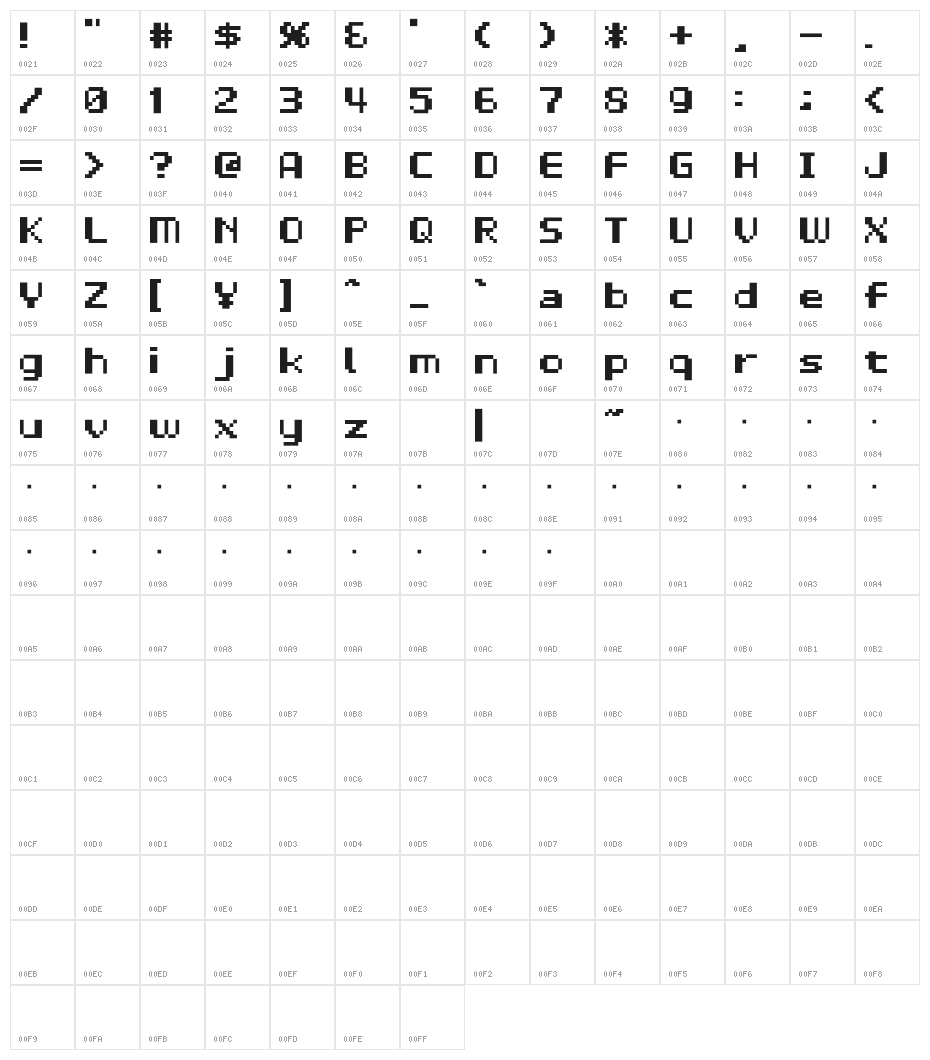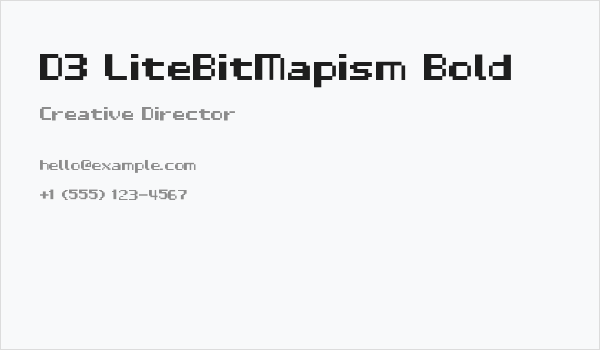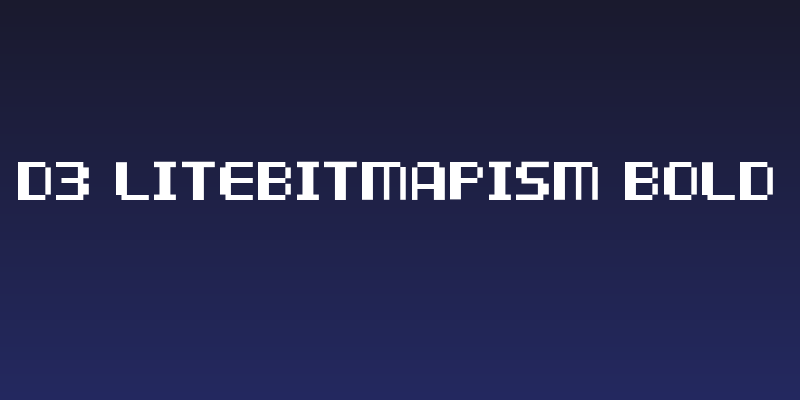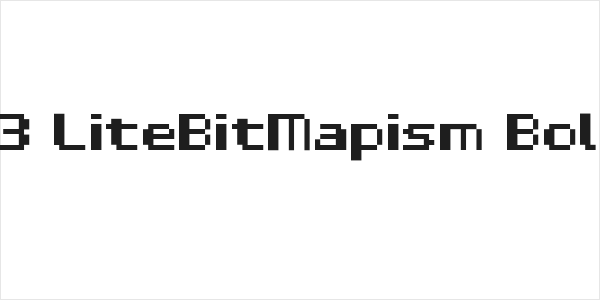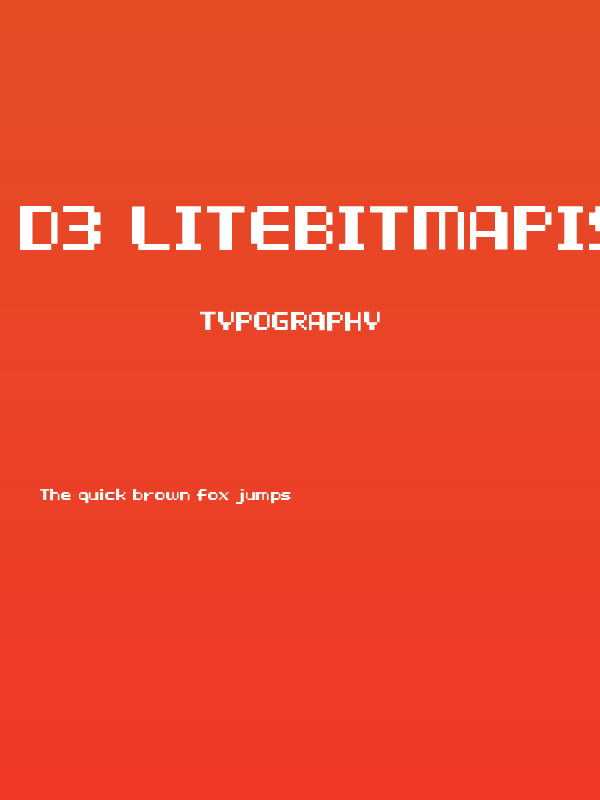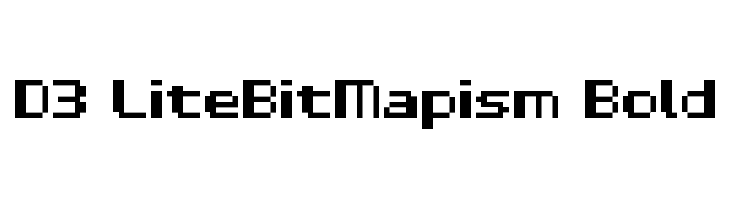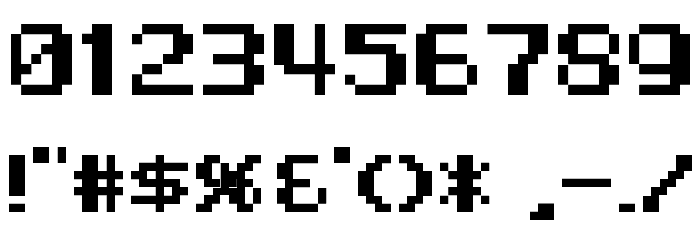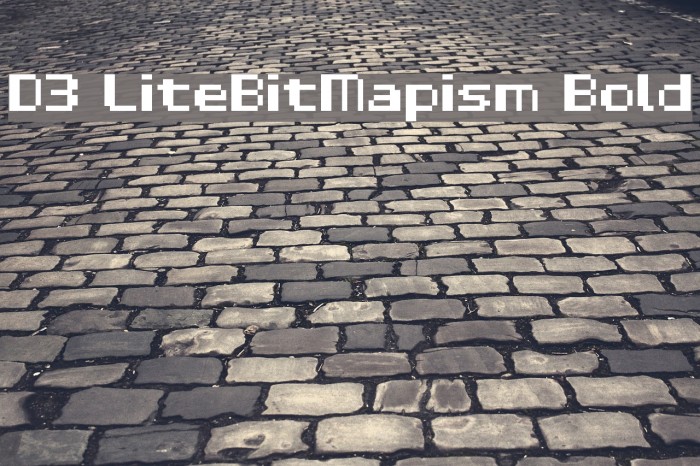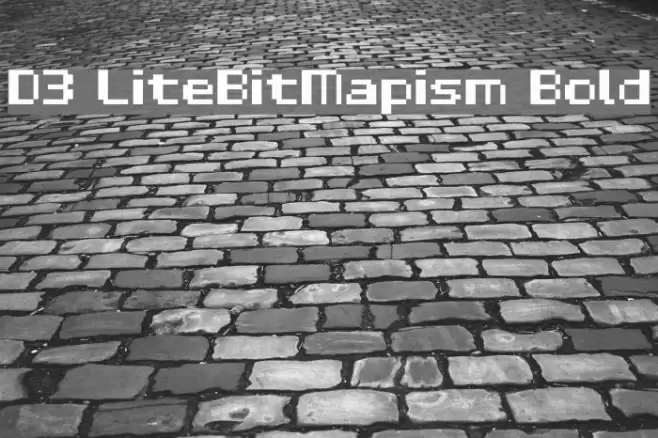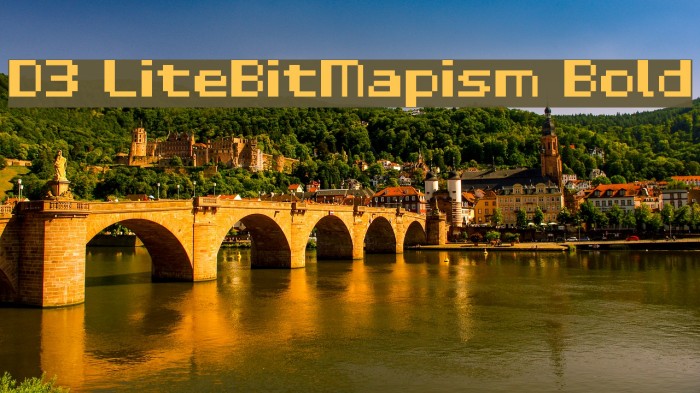
D3 LiteBitMapism Bold Font
| श्रेणियाँ | Pixel |
| समग्र शैली | Retro, Digital |
| उपयोग का मामला | Headlines, Logos, Digital Art |
| सुझाए गए प्रोजेक्ट | Ideal for video game designs, retro-themed posters, digital art, and any project seeking a nostalgic, tech-inspired look. |